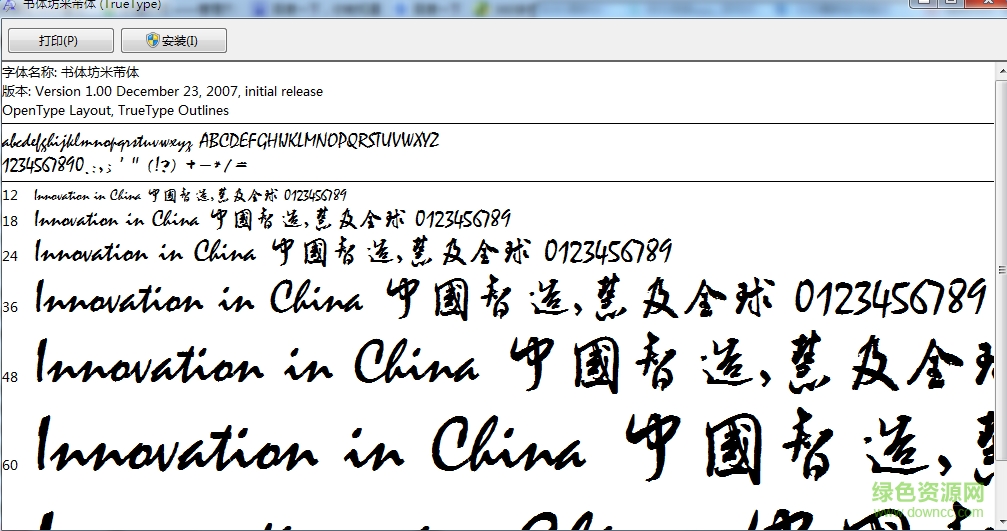
書體坊米芾體字體是一款根據(jù)中國著名書法家米芾的書法制作的電腦字體,字形非常的優(yōu)美,具有藝術性,感興趣的朋友歡迎來綠色資源網(wǎng)下載試用!
書體坊米芾體字體是一款模仿著名書法家藝術家米芾書法作品的漢字字體,字體以楷、行、草、蒃、隸等多種字體,組成,適用于多用于平面設計,商標設計等商業(yè)場用途上,是廣告從業(yè)人員必備的中文字體。